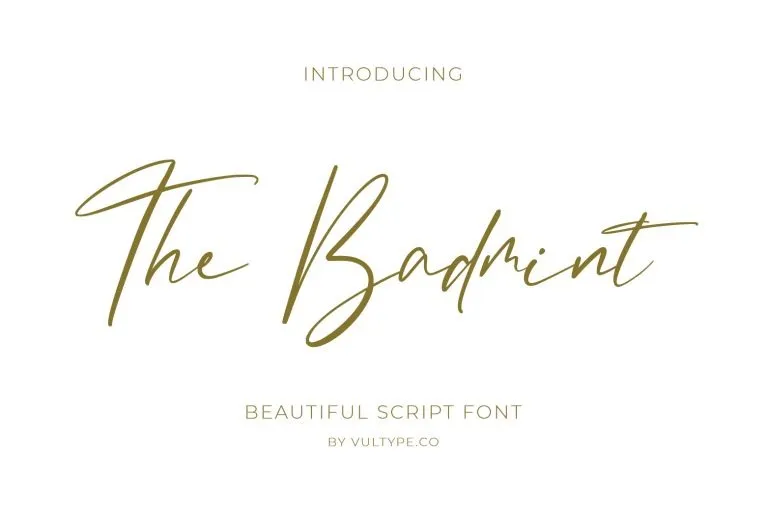
The Badmint Font – Download Grátis
A fonte “The Badmint Font” é uma tipografia moderna criada pela hugefonts para designers de todo mundo. Esta seleção de scripts está perfeita para branding, oferecendo um estilo limpo e elegante que se destaca. Com sua aparência fina e suave, ela certamente faz jus a qualquer design ao qual você deseje incorporá-la. Seja para criar logos memoráveis ou elementos gráficos exclusivos, “The Badmint Font” não deixará você insatisfeito. Sua simplicidade única faz dela uma opção inteligente para designers em busca de algo que destaque sua produção gráfica.